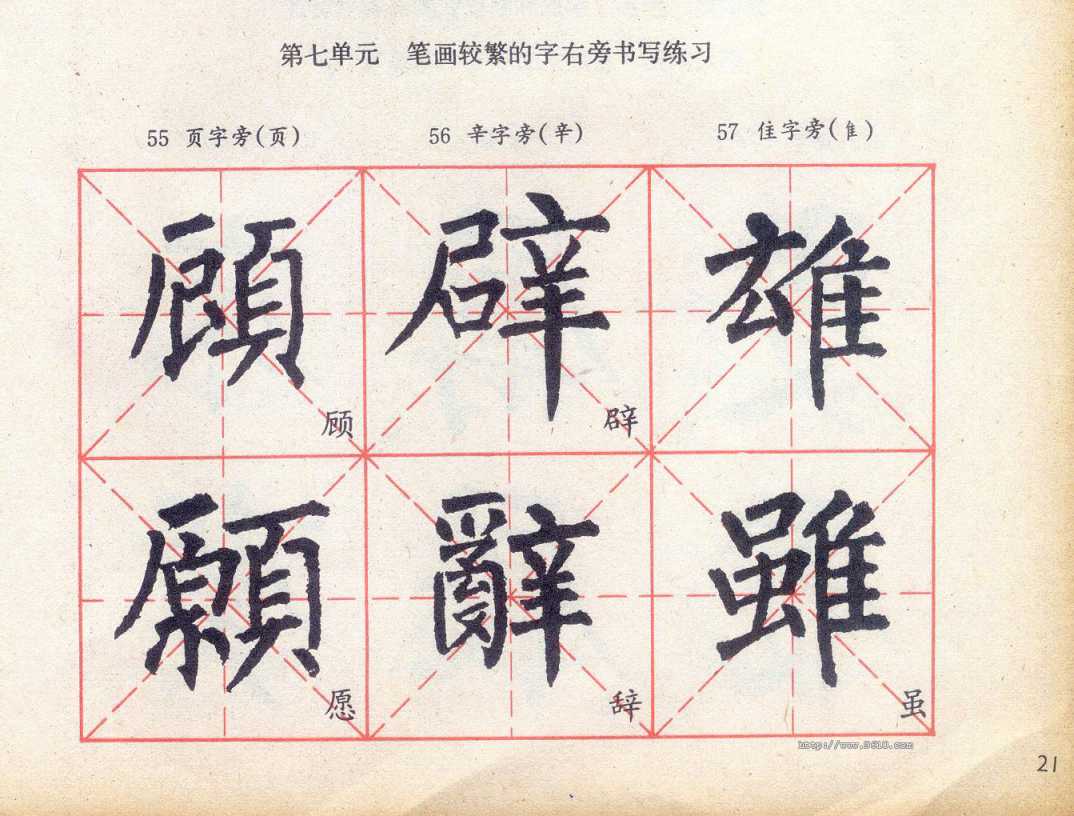
柳公权及其作品简介
柳公权(公元七七八年——八六五年),字诚悬,京兆华原(今陕西耀县)人,唐宪 宗元和进士,穆宗时以翰林院侍书学士再迁司封员外郎,累官太子少师,所以又称“柳 少师”。为人秉性刚直,从小工诗文,擅长篆、草、真,行,而对楷书致力尤深,是晚唐 时期的大书法家。
他的书法,初学二王(即王羲之和王献之父子),随后遍习隋唐以来楷法,所以他的 作品,既具有魏晋人的风貌和隋龙藏寺碑的瘦劲,又更多地吸取了初唐以来各家之长。 由于他受到盛唐时期的颜书孕育,所有转折钩挑以及撇捺等笔调,又大量地变用了颜法。 柳公权博采群美而融冶一炉,写出了结体疏朗,神气清健,方圆兼使,法度森严而又 富于变化的书体,与颜真卿同为有唐以来善于创新的一代宗匠。
同时,也正因为柳书有运古生新,遒媚兼备而平易近人的特点,所以也与颜书一样, 同为实用价值较高的书体,影响后世极大,至今不衰。特别在唐人楷书中,柳公权和颜 真卿都好以大楷书写碑文,字体既能展写为榜书,又能缩写为中、小楷书。所以柳体历 来就风靡各地,甚至传播到日本等国。在我国一向被选用为初学楷书的范本,以此作为 端正字形,练习楷书基本功的比较容易入门的好教材。